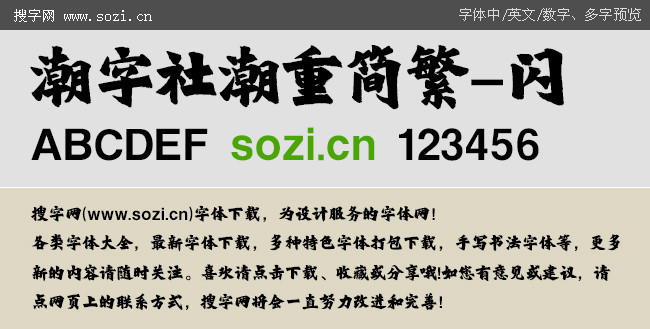
潮字社潮重簡(jiǎn)繁-閃
搜字網(wǎng)提供一款潮字社潮重簡(jiǎn)繁-閃中文字體下載,潮字社潮重簡(jiǎn)繁-閃是一款讓人賞心悅目、百看不厭的中文書法字體,字體厚重大方,效果嚴(yán)謹(jǐn)大氣,可用于出版和印刷,文學(xué)雜志,海報(bào)設(shè)計(jì)等應(yīng)用。(本字體為個(gè)人非商用版,商用請(qǐng)聯(lián)系作者購(gòu)買授權(quán))